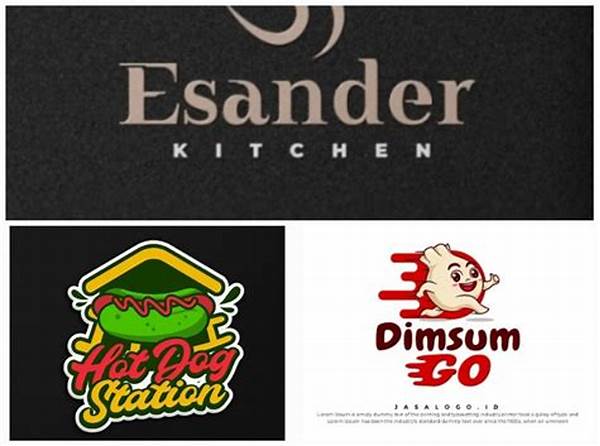
Halo teman-teman desainer! Kita semua tahu bahwa tren terus berubah, dan salah satu yang paling dinamis adalah tren font desain logo. Font bukan lagi sekadar huruf atau angka yang membentuk sebuah nama, tapi juga bagian dari identitas yang bisa membuat logo jadi lebih menonjol. Sebagai desainer, penting bagi kita selalu update dengan tren yang sedang populer, bukan? Nah, mari kita bahas lebih lanjut!
Evolusi Tren Font Desain Logo
Sebelum kita masuk ke detail, mari kita lihat dulu bagaimana tren font desain logo telah berevolusi. Dari font serif yang klasik hingga gaya sans-serif yang minimalis, setiap tahun ada saja yang baru. Misalnya, di era digital sekarang ini, font-display sering digunakan untuk memberikan tampilan yang lebih modern dan stylish. Namun, bukan berarti desain vintage tidak laku. Banyak brand besar yang justru kembali ke akar dengan menggunakan font retro. Tentu saja, semua ini disesuaikan dengan citra brand yang ingin dibentuk.
Salah satu hal menarik adalah penggunaan variable fonts yang kini semakin marak. Ini adalah teknologi baru yang memungkinkan perubahan berat dan gaya font dalam satu file saja. Ini benar-benar membuka banyak kemungkinan dan menambah fleksibilitas dalam desain. Tak hanya itu, font multi-bahasa kini menjadi sorotan, khususnya bagi brand yang beroperasi secara global. Dengan demikian, kebutuhan akan font yang mendukung banyak karakter semakin meningkat.
Jadi, apa yang membuat tren font desain logo begitu menarik? Mungkin karena setiap font adalah cerita baru yang bisa dipakai untuk menggambarkan keunikan suatu brand. Pergantian tren ini seperti me-refresh tampilan dunia desain dari tahun ke tahun. Font yang tepat bisa membuat sebuah logo berbicara banyak tanpa harus menulis panjang lebar. Itulah kekuatan grafis yang sesungguhnya!
Mengapa Tren Font Desain Logo Begitu Penting?
Pertanyaan bagus! Kenapa sih tren font desain logo dianggap penting?
1. Pencitraan Brand: Setiap font punya karakter unik yang bisa memperkuat pesan sebuah brand.
2. Daya Tarik Visual: Font baru memberikan tampilan segar yang menarik perhatian.
3. Fleksibilitas: Dengan teknologi, font kini lebih mudah dimanipulasi untuk berbagai kebutuhan.
4. Perubahan Pasar: Tren yang up-to-date mencerminkan bahwa brand Anda tidak ketinggalan zaman.
5. Komunikasi Efektif: Memudahkan untuk menyampaikan pesan secara visual.
Dengan memahami tren font desain logo, kita bisa membuat pilihan yang lebih tepat dan strategis.
Tren Font Desain Logo & Pilihan Gaya
Nah, berbicara tentang pilihan gaya, tren font desain logo saat ini sangat bervariasi lho. Mulai dari gaya minimalis hingga dekoratif yang penuh detail. Sebuah font bisa menciptakan mood atau perasaan tertentu, misalnya font yang tebal memberikan kesan kuat dan tegas, sementara font tipis bisa memberikan kesan elegan dan modern. Selain itu, tren saat ini juga menyukai eksperimen dengan kombinasi warna dan struktur huruf yang unik.
Menariknya, tren font desain logo juga mengadopsi elemen-elemen dari budaya pop. Gaya yang terinspirasi dari video game, film, dan musik sering kali muncul dalam desain logo, membuatnya lebih relevan dan relatable bagi audiens khususnya generasi muda. Inilah yang membuat sebuah logo menjadi lebih dari sekedar penanda, tapi juga pernyataan.
Tentu saja, tren bukanlah satu-satunya faktor yang harus menjadi pertimbangan. Anda tetap harus memahami identitas brand dan audiens yang ingin diraih. Jadi, tetap kreatif dan jangan takut berinovasi!
Tips Memilih Font dalam Tren Font Desain Logo
Memilih font yang tepat tidaklah mudah, terlebih dengan berbagai pilihan dalam tren font desain logo. Berikut beberapa tips yang bisa Anda ikuti:
1. Kenali Brand dan Audiens: Pastikan font yang dipilih sesuai dengan identitas brand dan target pasar.
2. Uji Konsistensi dan Fleksibilitas: Cek bagaimana font tampil dalam berbagai ukuran dan media.
3. Pantau Update Tren: Selalu ikuti perkembangan tren agar desain tetap relevan.
4. Eksplorasi Kombinasi Font: Coba berbagai kombinasi font untuk mendapatkan hasil yang fresh.
5. Kesederhanaan Adalah Kunci: Jangan terlalu rumit, pilih font yang mudah dibaca.
6. Perhatikan Ragam Huruf: Font harus punya ragam huruf yang lengkap, termasuk aksen.
7. Keberlanjutan: Pilih font yang bisa bertahan lama dan tidak mudah ketinggalan zaman.
8. Gunakan Alat Bantu: Manfaatkan software desain untuk melihat preview font.
9. Pertimbangkan Teknologi Baru: Seperti variable fonts untuk fleksibilitas lebih.
10. Selalu Tes: Lakukan testing dengan mengaplikasikan font pada logo untuk melihat hasil akhirnya.
Keberlanjutan dalam Tren Font Desain Logo
Seiring dengan perubahan tren, aspek keberlanjutan juga menjadi pertimbangan penting dalam tren font desain logo. Di tengah meningkatnya kesadaran lingkungan, memilih font yang efisien untuk digunakan dalam berbagai media digital bisa menjadi keputusan yang bijaksana. Font yang dirancang dengan baik dapat mengurangi penggunaan memori dan waktu loading, yang pada akhirnya juga menurunkan jejak karbon digital.
Bagi desainer, memahami tren ini adalah soal mencari keseimbangan antara estetika dan fungsionalitas. Tidak setiap tren harus diikuti, namun memiliki pengetahuan yang luas tentang pilihan dan arah tren akan membantu Anda membuat keputusan yang lebih tepat. Pada akhirnya, tren font desain logo adalah tentang inovasi dan bagaimana kita bisa menggunakan elemen ini untuk menciptakan karya yang tidak hanya menarik, tetapi juga berkesan dan relevan. Tetaplah bersemangat dalam setiap desain yang Anda buat, dan jadikan font sebagai sahabat baru Anda dalam berkreasi!